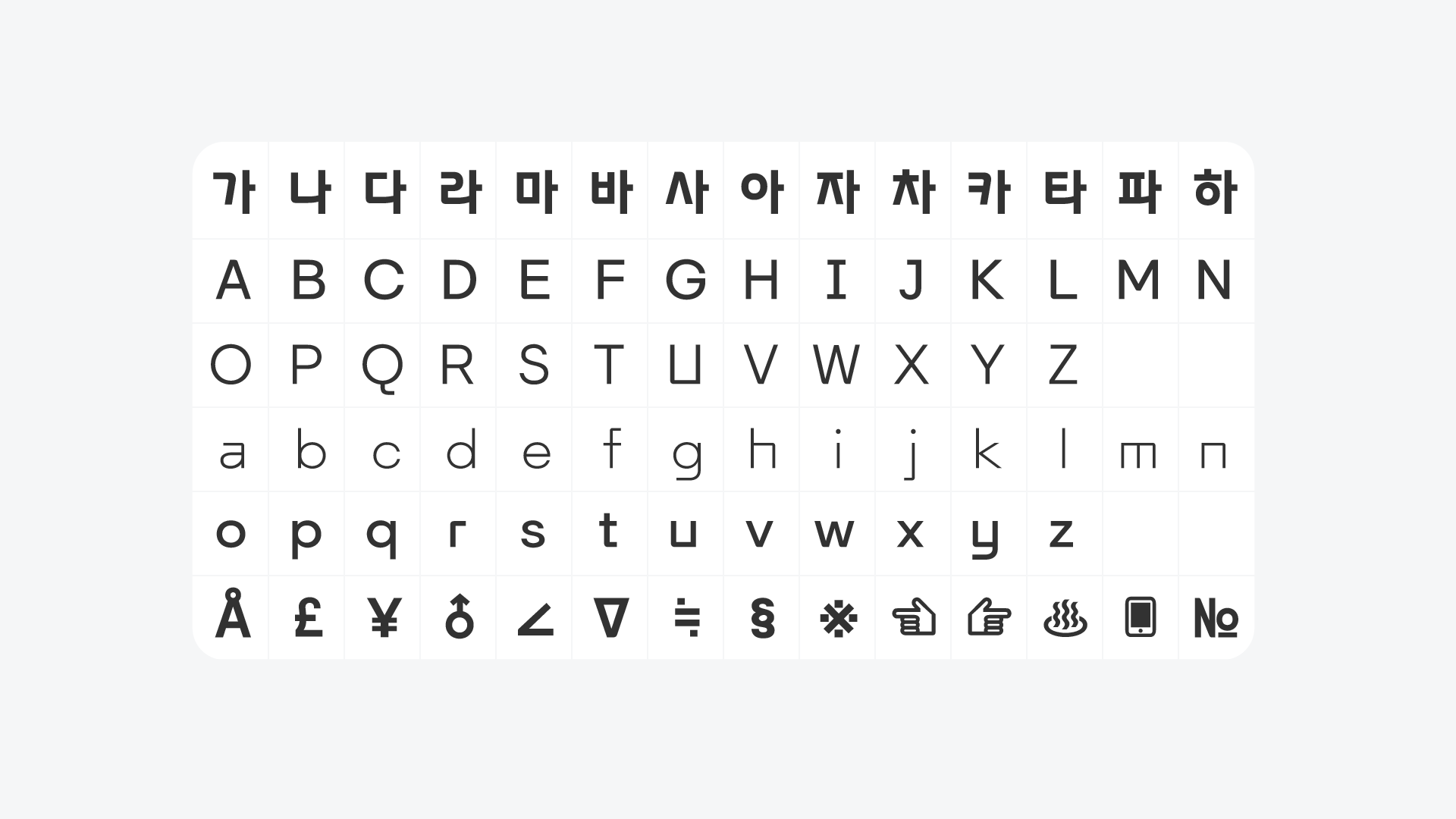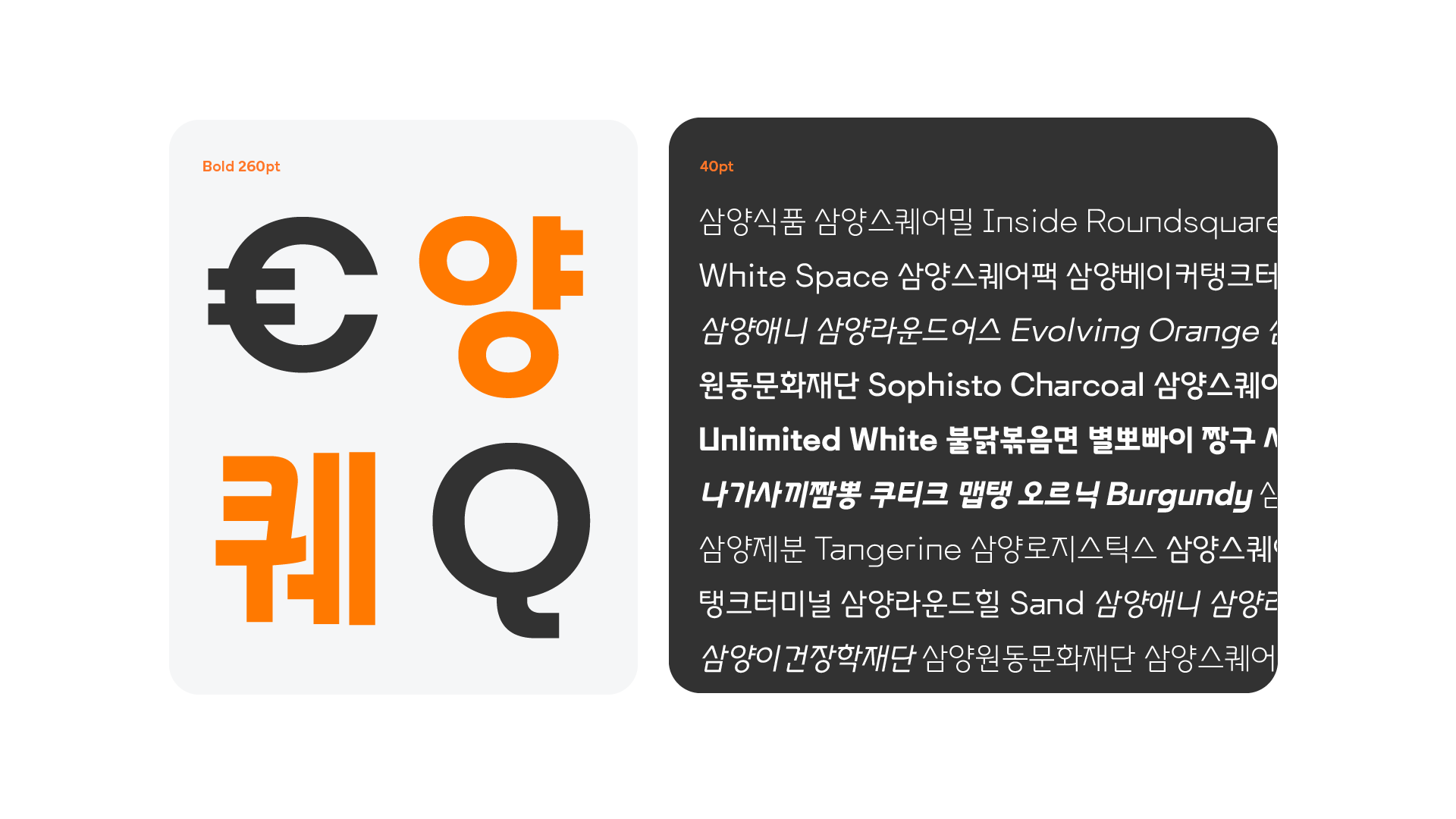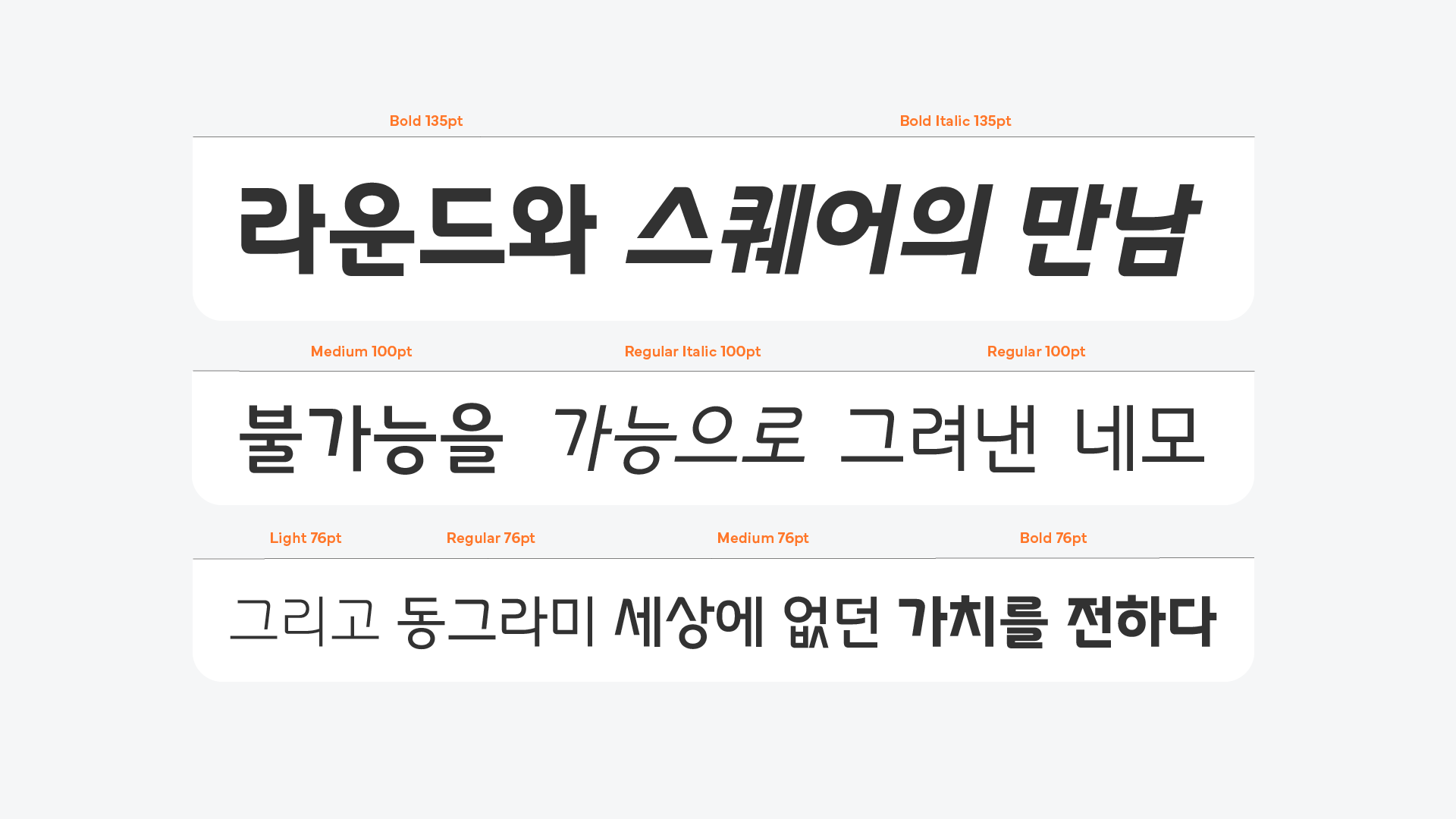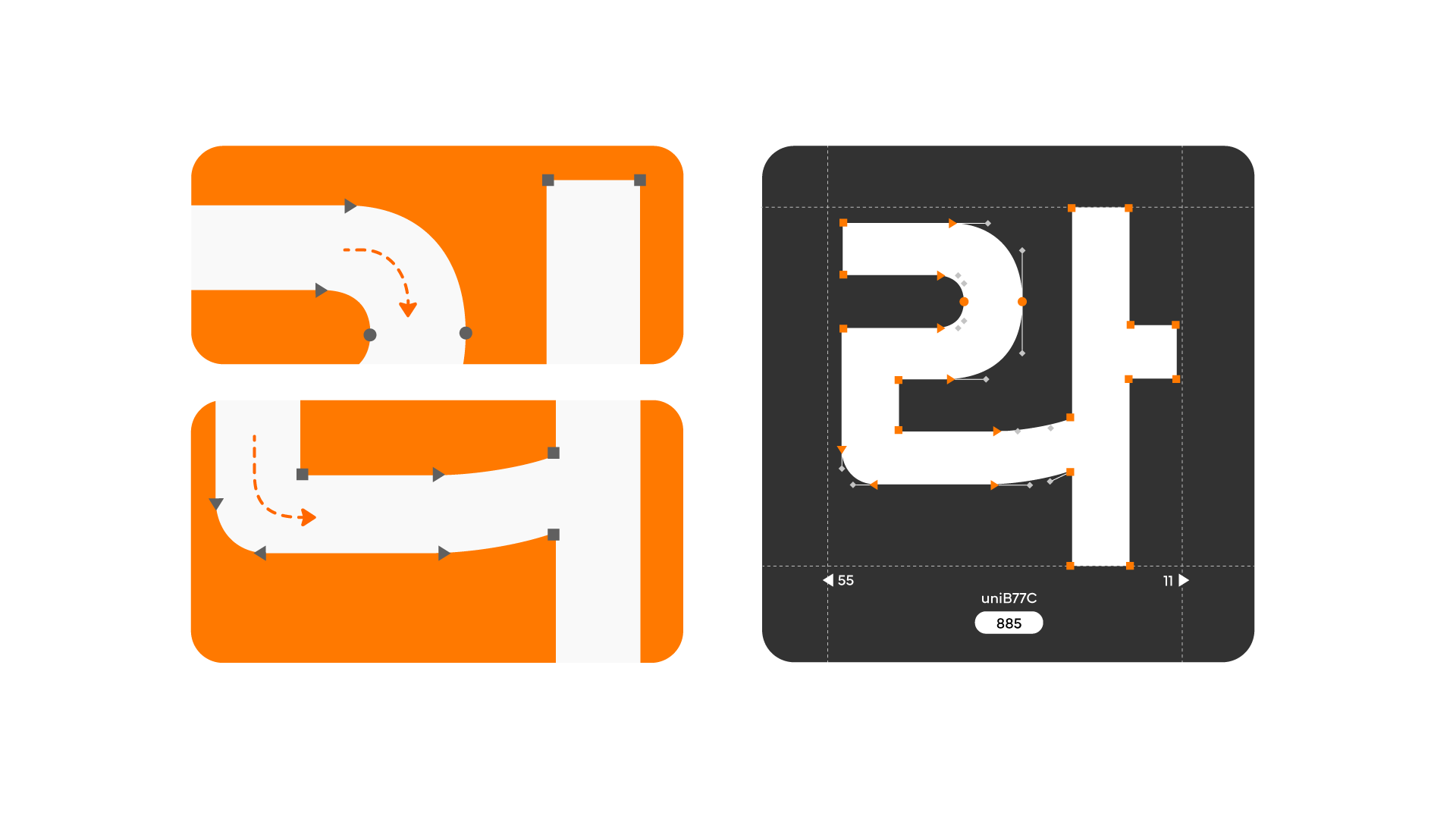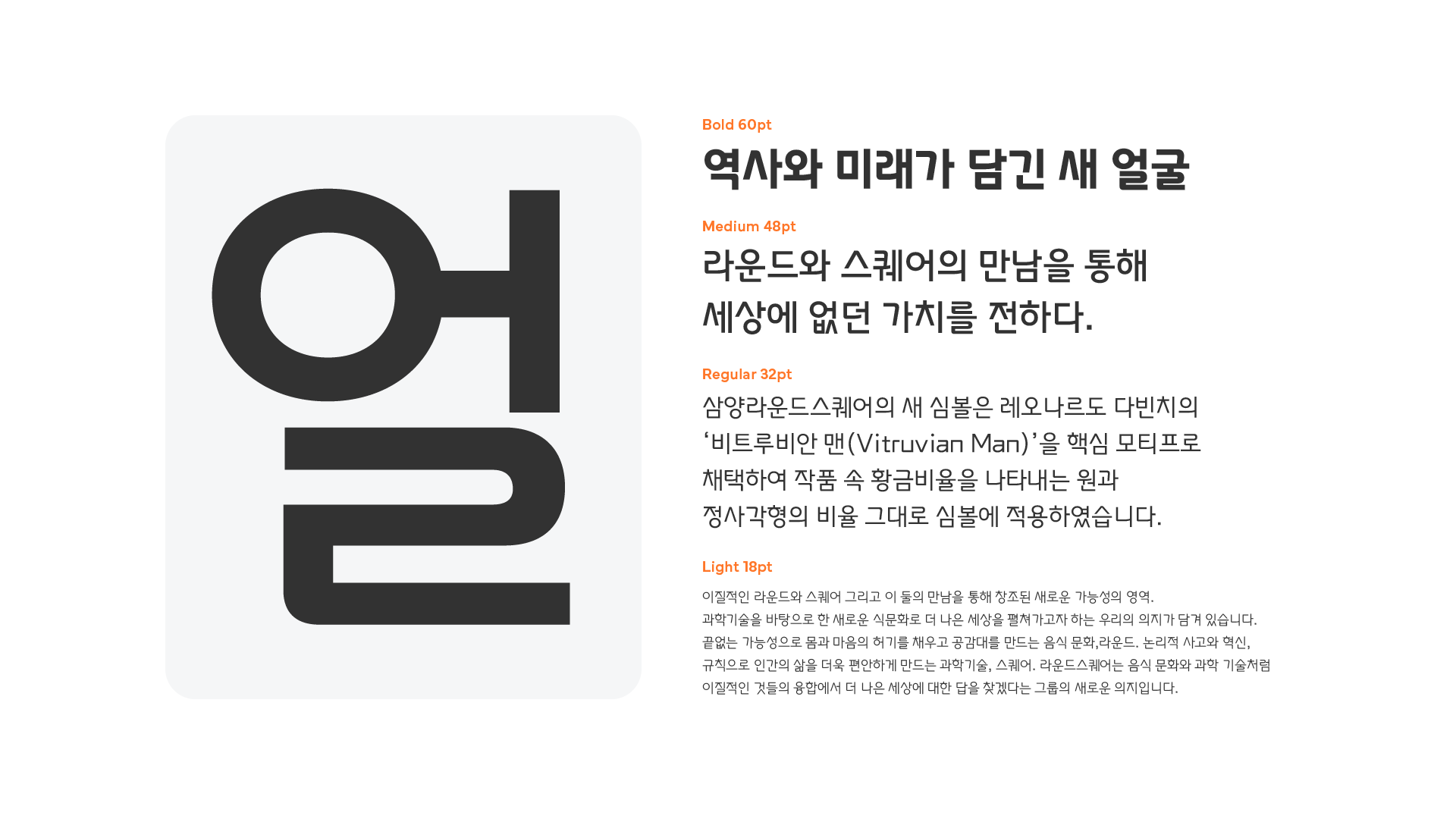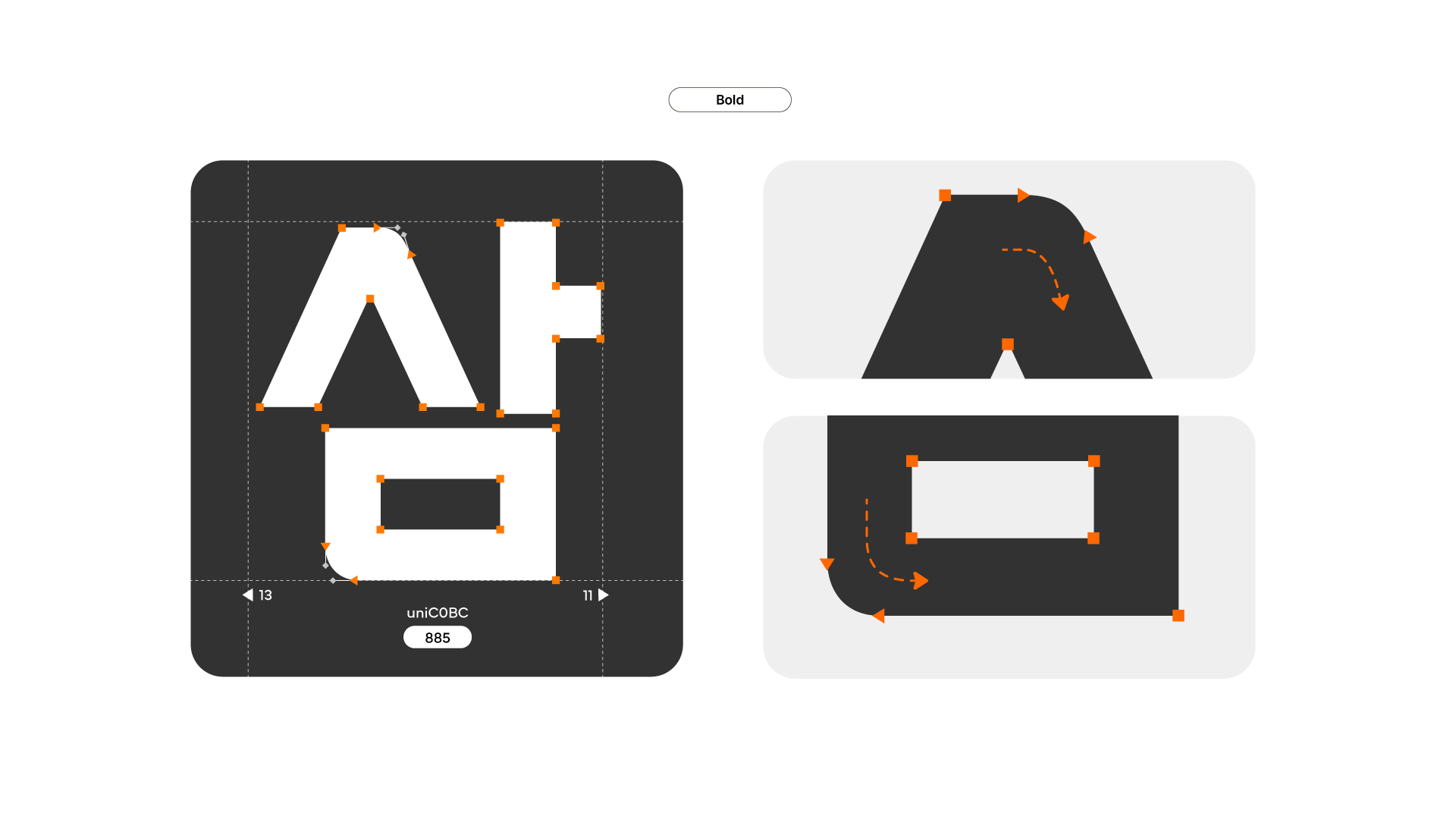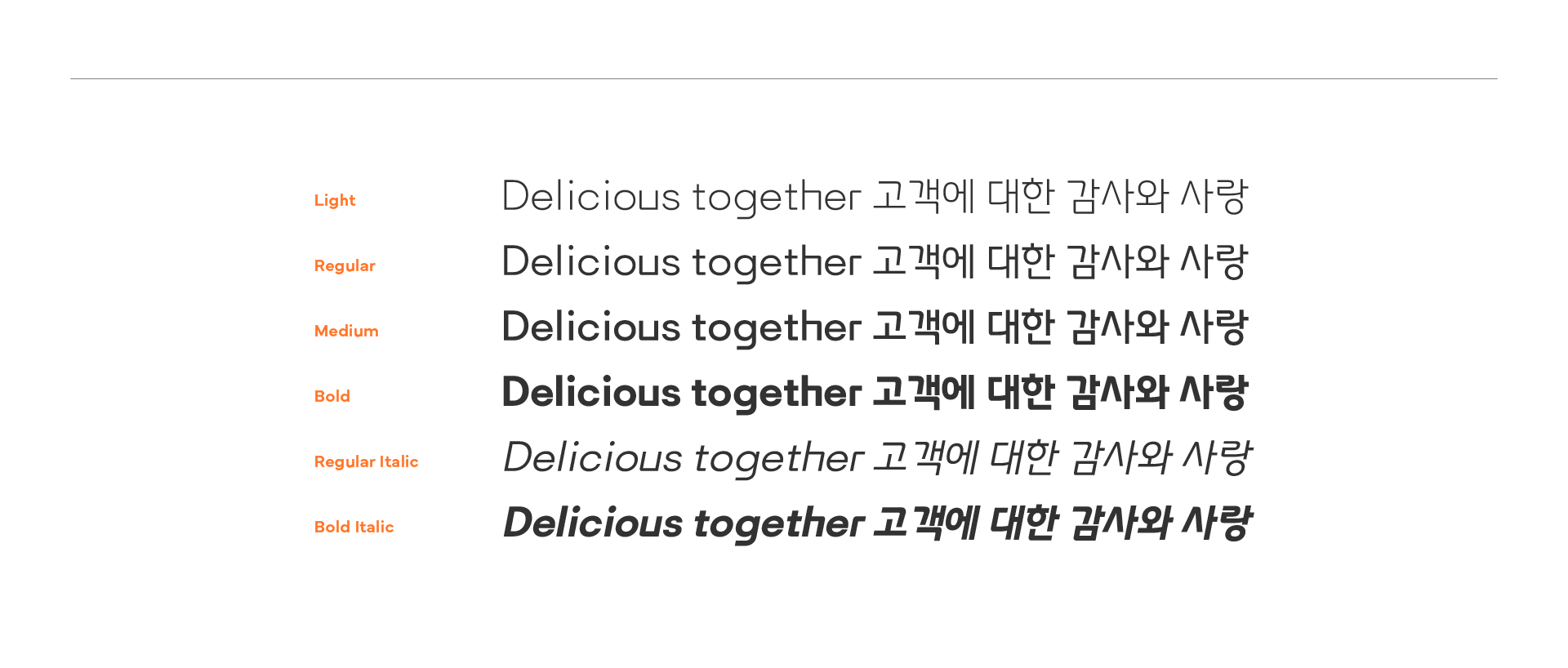
삼양 라운드스퀘어의 영문 로고타입 디자인을 반영하여 한글 이미지를 담아냈습니다. 원형과 사각형에서 볼 수 있는 기하학적 형태를 표현하였습니다.
삼양 라운드스퀘어의 영문 로고타입 디자인을 반영하여 한글 이미지를 담아냈습니다.
원형과 사각형에서 볼 수 있는 기하학적 형태를 표현하였습니다.
서체 이름
Roundsquare Sans